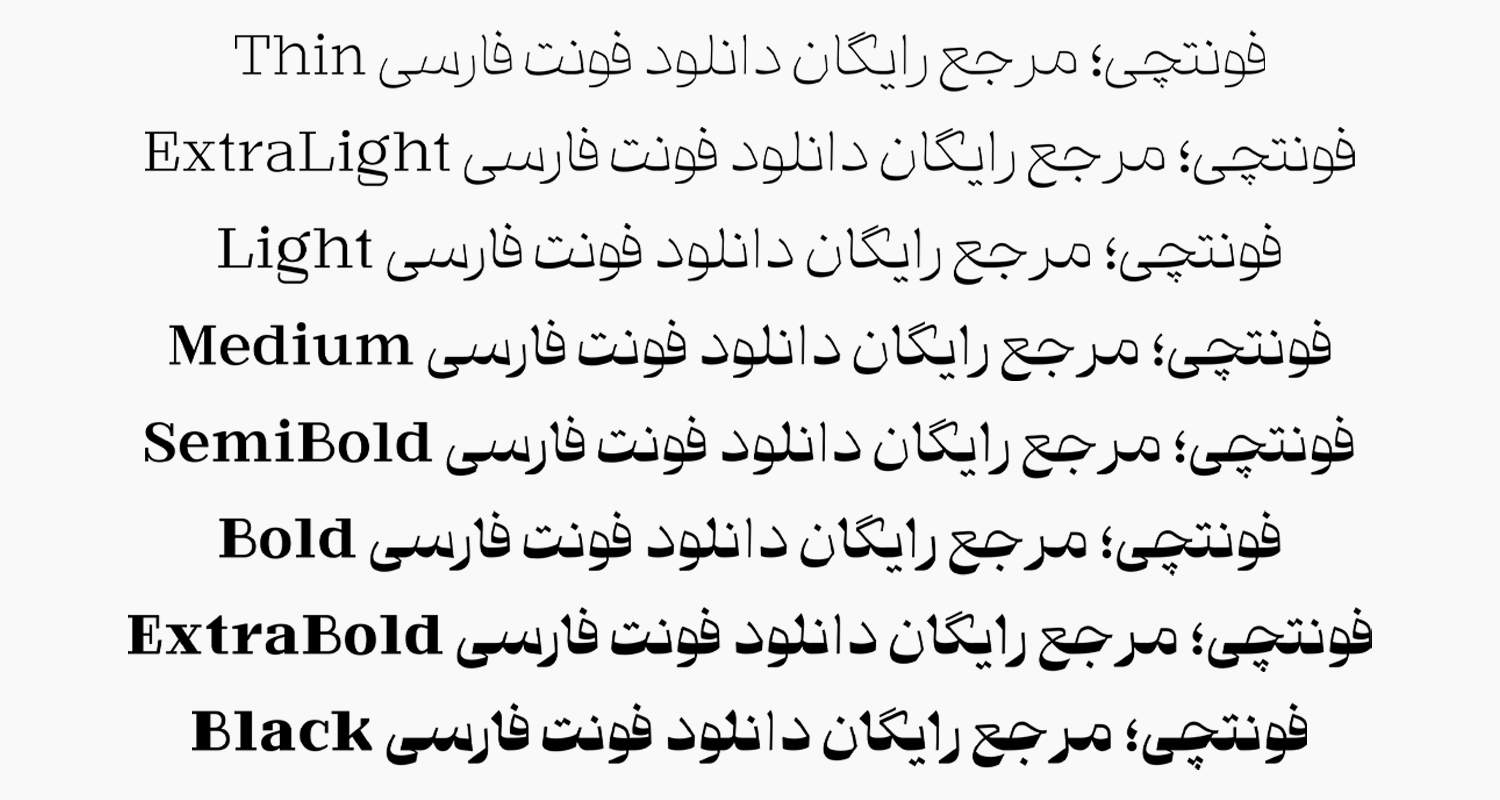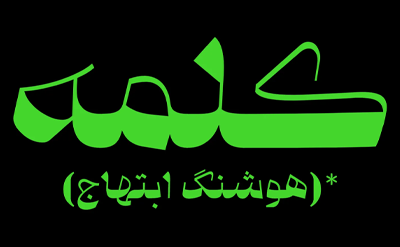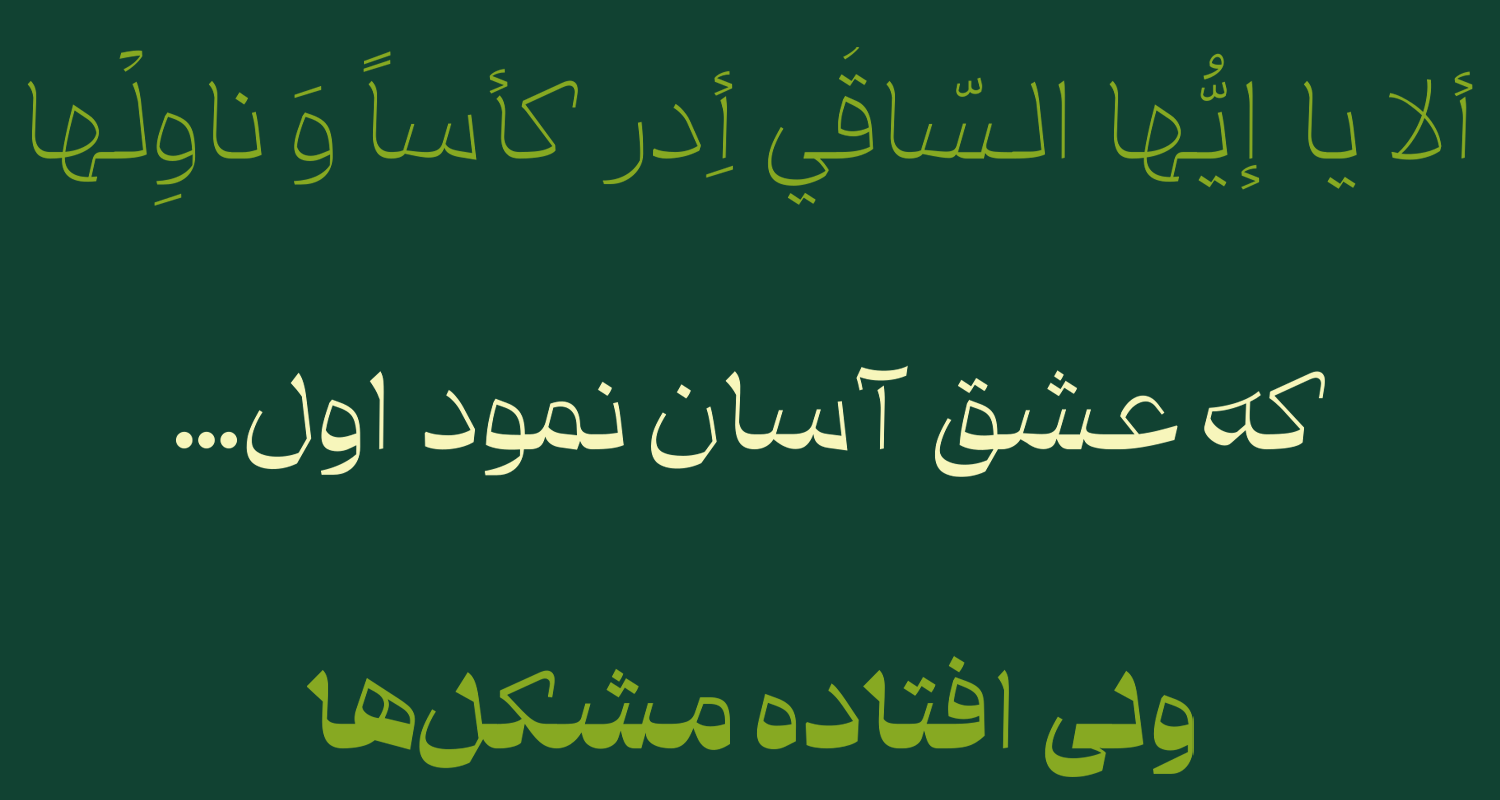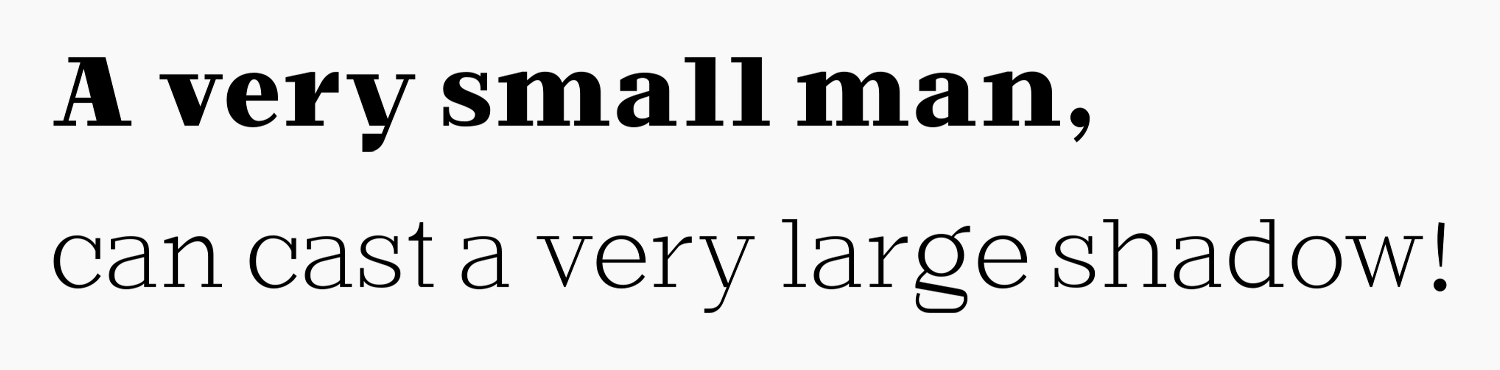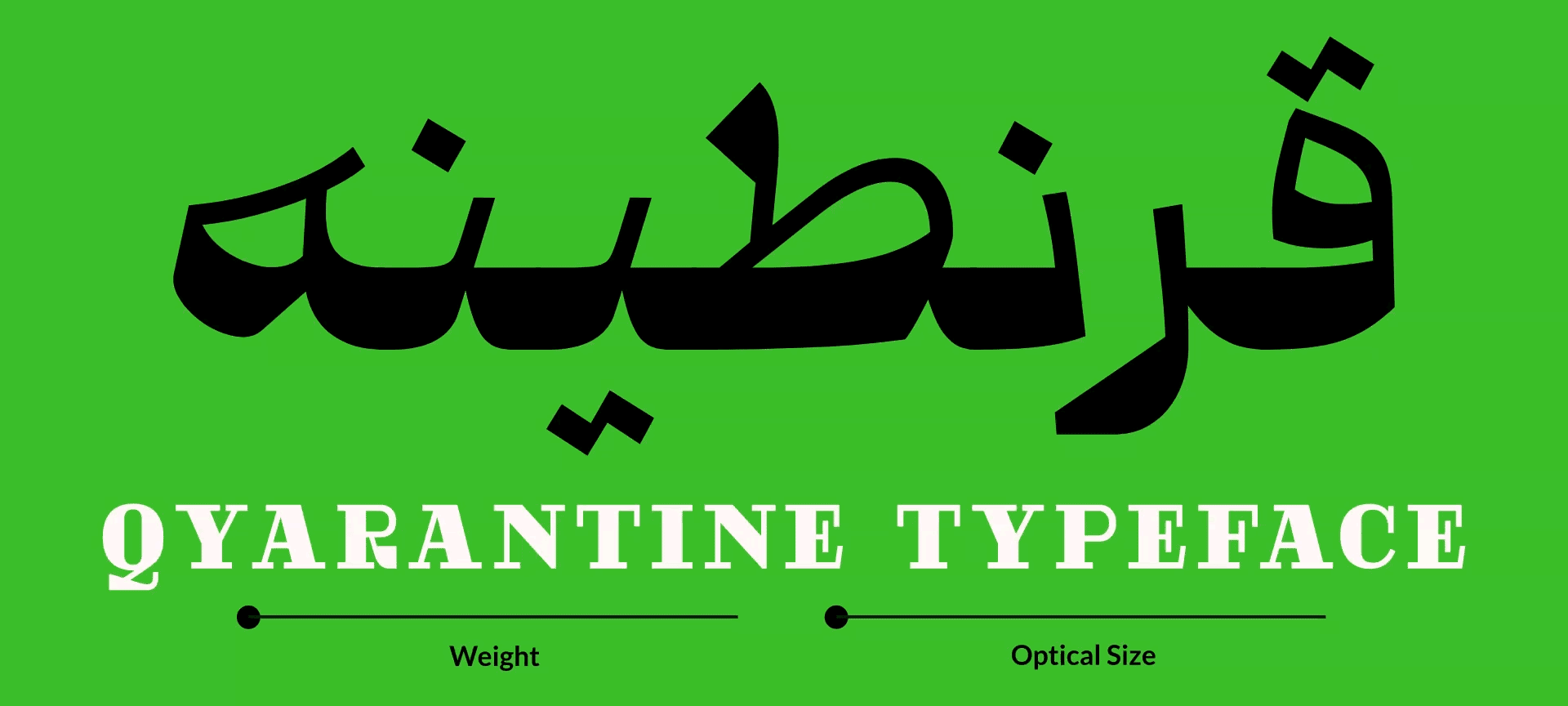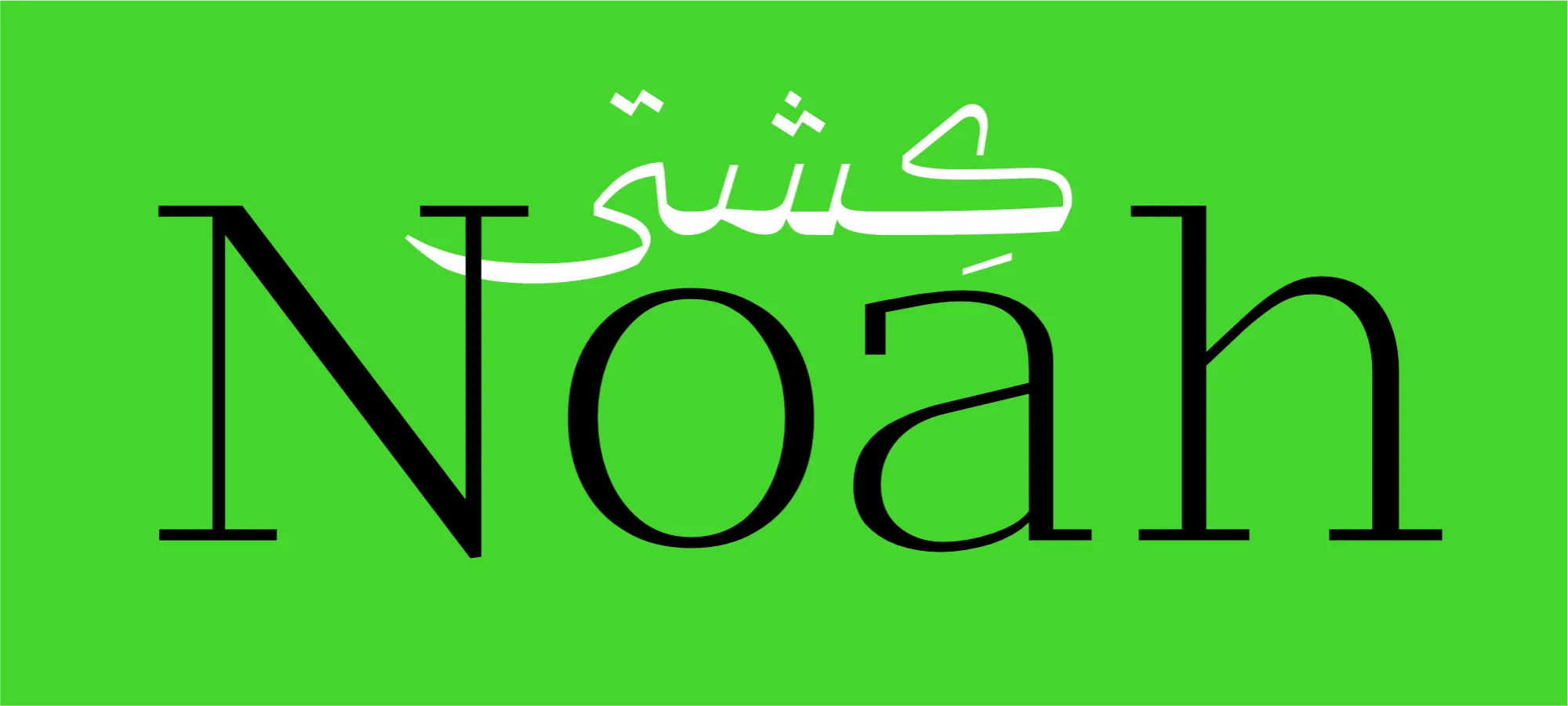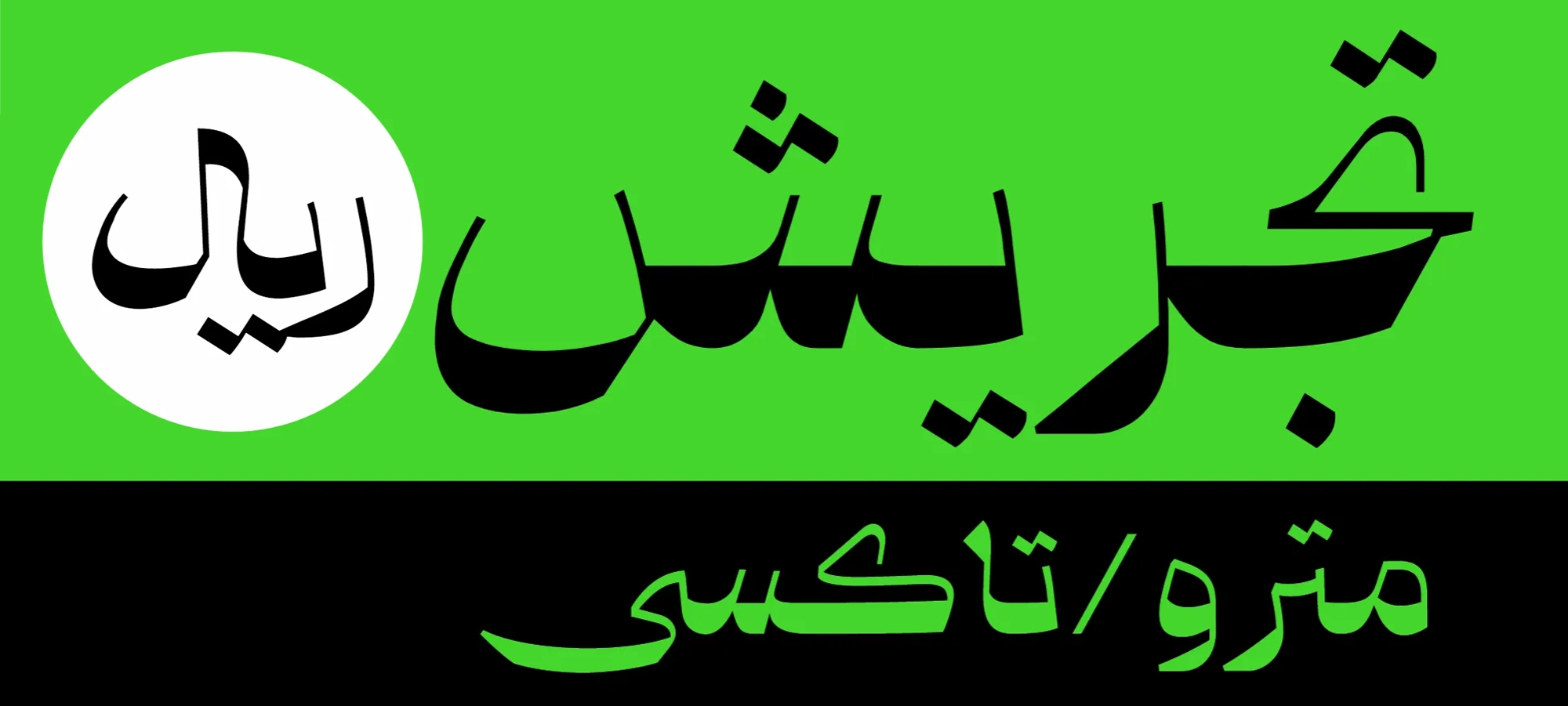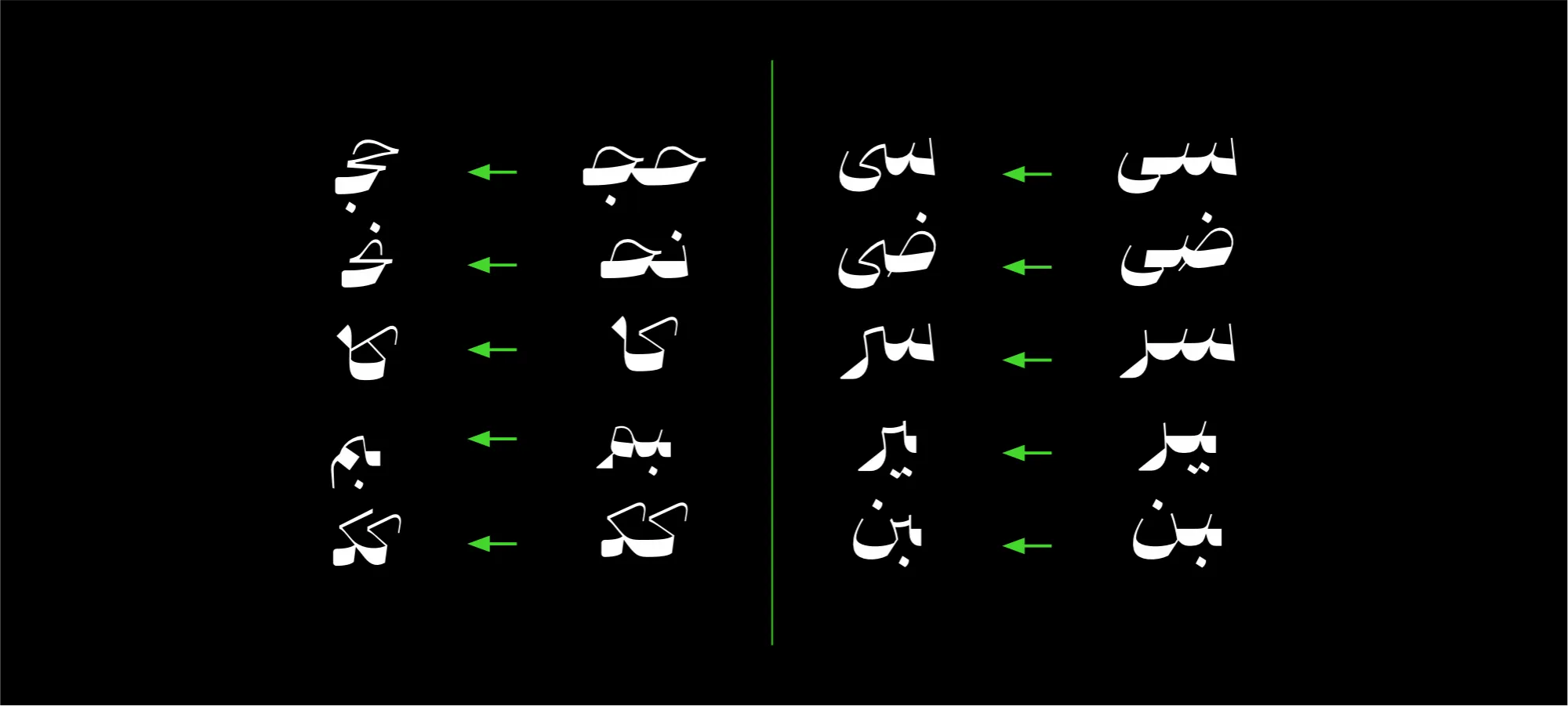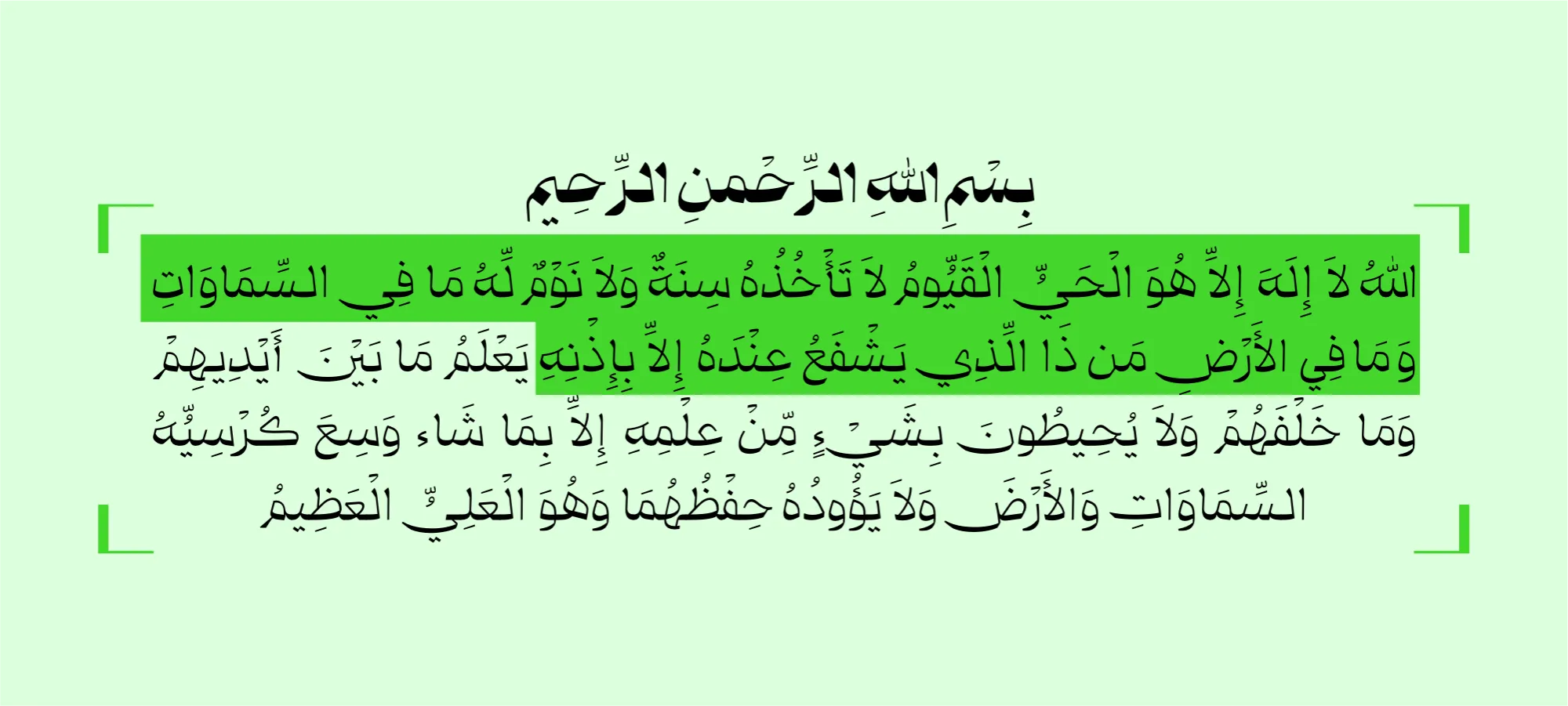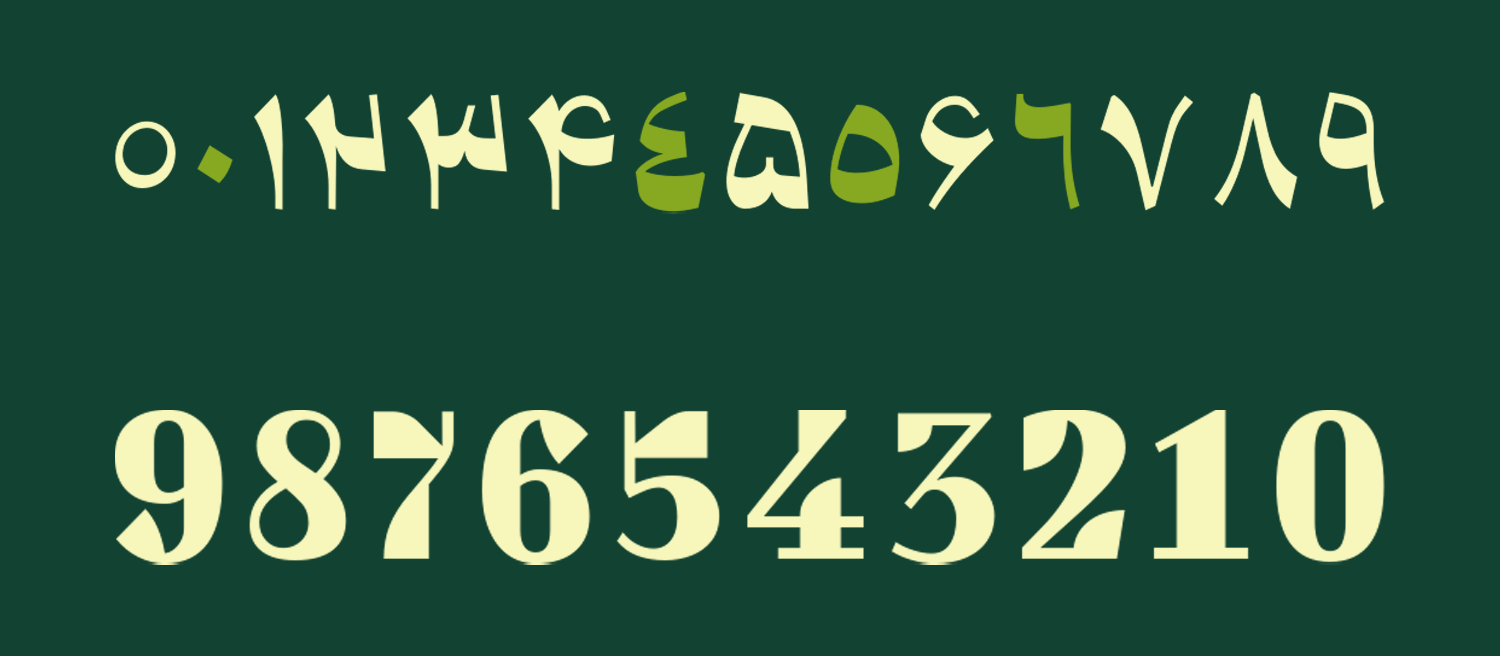
فونت قرنطینه (Quarantine)
فونت قرنطینه (به انگلیسی: Quarantine) از دیگر فونتهای فارسی مناسب برای عناوین و تبلیغات است که از ۹ وزن مختلف در قالب ۴ سبک مختلف پشتیبانی میکند. این فونت خاص که ساختاری کاملا هندسی دارد، به سبک خط قدیمی نسخ طراحی شده است که ظاهر زیبایی به عناوین، خصوصا در سایزها و وزنهای بزرگ خواهد داد.
این فونت توسط محمدرضا چیت ساز در سال ۱۴۰۰ و در زمان همهگیری بیماری کرونا شکل گرفت که پس از نزدیک به دو سال کار بر روی این فونت در نهایت در تابستان ۱۴۰۲ به شکل امروزی خود در آمد. این فونت در سبک خط نسخ نمایشی طراحی شده که برای عناوین و متنهای کوتاه بهترین خروجی را از خود به نمایش میگذارد.
در ادامه این نوشته از سایت فونتچی به نقد و بررسی فونت جدید قرنطینه خواهیم پرداخت؛ فونتی که با وزنهای ۹ گانه خود و در کنار آن پشتیبانی از نسخه وریبل و همچنین ترکیبات جایگزین که برخی از آنها اختیاری و برخی اجباری هستند، ظاهر خارقالعادهای به متون فارسی و لاتین شما خواهد داد.
بررسی و دانلود فونت قرنطینه (Quarantine) وریبل
فونت قرنطینه با لحن جسور و شخصیت خاص خود، به آسانی در هر نوع اثر تبلیغاتی خود را به رخ میکشد. این قلم تلفیقی از هندسه و خوشنویسی است که خروجی نهایی آن را چیزی معادل نسخ نمایشی میبینیم. جزییات دقیق و ظرافتهای منحصر به فرد فونت قرنطینه به ویژه در سایزهای بزرگ و تیترها برجسته میشود.
سبک طراحی و وزن فونت قرنطینه
در طراحی فونت قرنطینه استایل Optical Size در نظر گرفته شده که کمک میکند متناسب با سایز نوشته، مقدار کنتراست ضخامت را کنترل کنید.
طراحی خلاقانه و ابداع فرمهای نوین از ویژگیهای بارز فونت قرنطینه محسوب میشوند. تمرکز بر استفاده از سطح در مقایسه با دور و برجستهسازی شکستگیها در برابر منحنیها و همچنین رفتار پویا در تغییر ضخامت حروف، هیجان و جاذبهای خاص به این فونت بخشیده است.
در فونت Quarantine چهار سبک در نظر گرفته شده است که ضخامت خطوط باریک را تعیین میکند. برای نمایش بهتر خطوط باریک در سایزهای کوچک، توصیه میشود که از مقدار کمتر برای optical size استفاده گردد. این سبکها در ۸ وزن مختلف نازک تا سیاه را شامل میشود که میتوانید در متون کوتاه تا بلند از آن استفاده کنید.
پشتیبانی از ۳ زبان متنوع
این فونت فارسی از زبانهای عربی و انگلیسی نیز پشتیبانی کامل دارد. طراحی تمامی حروف و گلیفها در این فونت دارای ساختاری یکپارچه بوده و همان ساختار هندسی را با درونمایه نسخ نمایشی از خود به جای گذاشته است. با اینکه بخشی از بخشهای حروف دارای ضخامت باریک و کمی است، اما در عین حال بخشهای دیگر وزن ضخیمی را دارند.
در زبانهای فارسی و عربی که بر پایه رسم خط فارسی هستند، تمامی حروف و گلیفهای یکسان دارای طراحی یکپارچه هستند. در زبان عربی نیز برخی حروف نظیر «ک، ی، ه، ؤ، ئ» که ساختاری متفاوت نسبت به زبان فارسی دارند، گلیفهای خاص خود را دارند.
در تمامی حروف فارسی و عربی کلیه اعراب و کاراکترهایی نظیر «سکون، تشدید، تنوینها» در همنشینی درستی با هم قرار میگیرند. اینطور نیست که به حروف قبلی یا بعدی خود بچسبند.
این فونت از زبان لاتین انگلیسی نیز با همان سبک فارسی پشتیبانی میکند. در تمامی وزنها و سبکهای ۸ گانه این قلم، حروف لاتین به گونهای طراحی شدهاند تا با حروف فارسی همخوانی داشته باشند. اندازهها، تراکمها و ویژگیهای طراحی حروف لاتین با حروف فارسی هماهنگ هستند و همنشینی زیبایی را به وجود میآورند.
فونت وریبل قرنطینه با ۲ متغیر
در نسخه وریبل فونت قرنطینه دو متغیر قرار گرفته است. متغیر اول مشابه تمامی فونتهای متغیر ساختار WEIGHT را تشکیل میدهد که به کمک آن میتوانید وزن فونت را با استفاده از کدهای CSS یا تنظیماتی که در open type برنامههای گرافیکی در نظر گرفته شده است تغییر دهید.
متغیر دیگر این فونت Optical Size است که در واقع همان تغییر کنتراست و ضخامت است. به کمک این متغیر میتوانید در ۴ سطح مختلف کنتراست فونت را در کلیه زوایا و چشمی حروف شخصی سازی کنید. این ویژگی برای مواقعی که از وزنهای مختلف فونت استفاده کنید کمک میکند تا خروجی کارتان از نظر زیبایی بسیار حرفهایتر جلوه کند.
فونت متغیر برای استفاده در سایت و همچنین نرمافزارهای گرافیکی پیشنهاد میشود که به وسیله آن میتوانید به جای نصب تکبهتک تمامی وزنهای ۸ گانه این قلم، صرفا با نصب یک فایل فونت به تمامی این وزنها دسترسی داشته باشید. جدایی از اینکه در استفاده از نسخه متغیر برای سایت، ضمن کاهش حجم فایل فونت، درخواستهای HTTP سرور به منظور افزایش سرعت نیز مزیت محسوب میگردد.
پشتیبانی از حروف جایگزین و حروف کشیده
در فونت قرنطینه این امکان را در اختیار دارید که حروف را به صورت کشیده استفاده کنید. کشیدگیها با بازنگری که از فرمهای کشیده خوشنویسی الهام گرفته شده، در این فونت گنجانده شده است. از این کشیدگیها میتوانید در حروف و ترکیبات مختلفی برای کنترل طول خطوط و زیبایی متون استفاده کنید.
استفاده از کشیدگیها در فونت قرنطینه کاملا اختیاری است که میتوانید در ترکیباتی مانند «ـی،ـن، ـس، ـک، ـب» با استفاده از قابلیت swash در نرم افزارهای گرافیکی آنها را فعال کنید. راهنمای استفاده از کشیدگی حروف در فونت قرنطینه درون بسته دانلودی فایل راهنما قرار گرفته شده است.